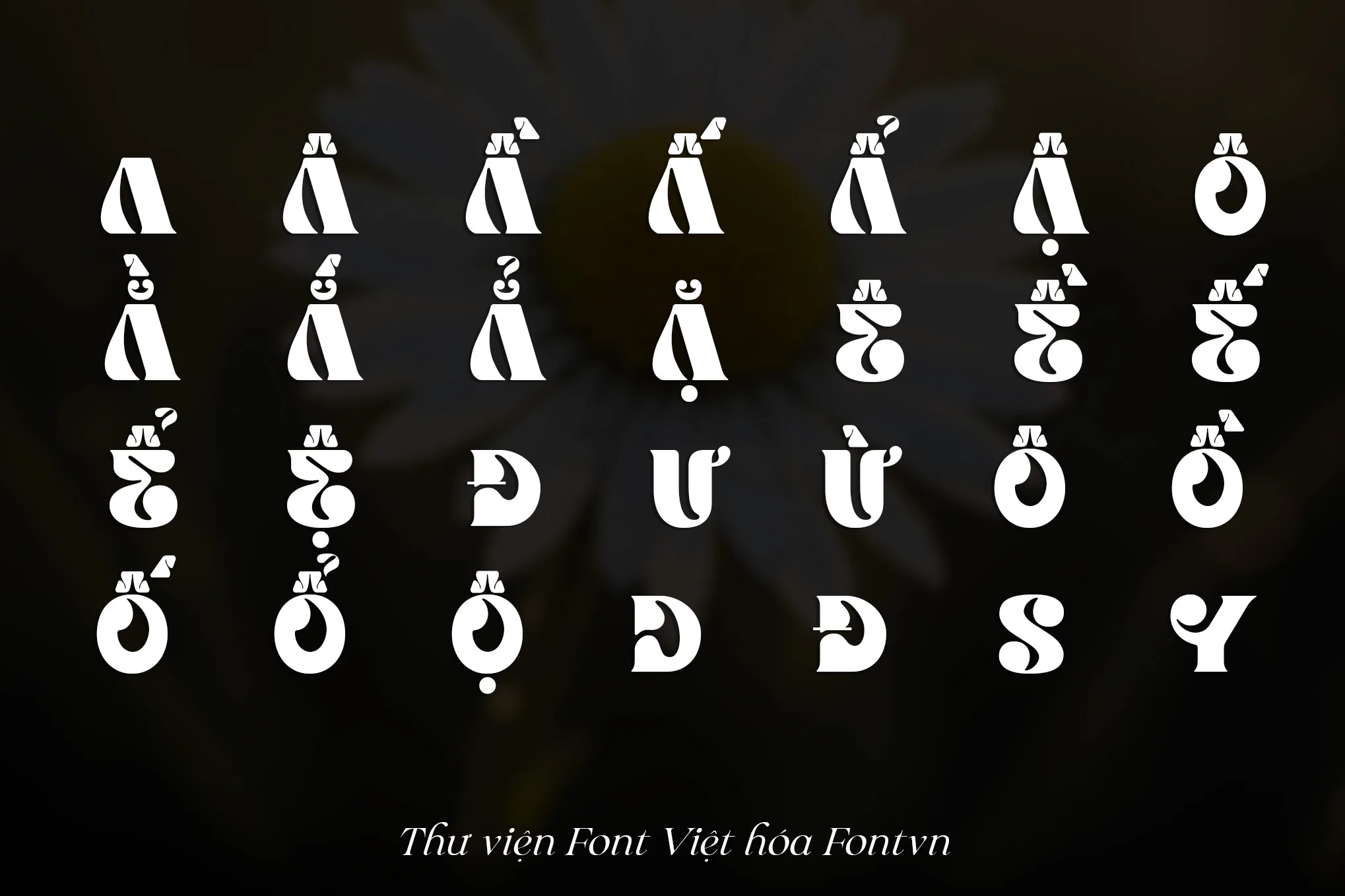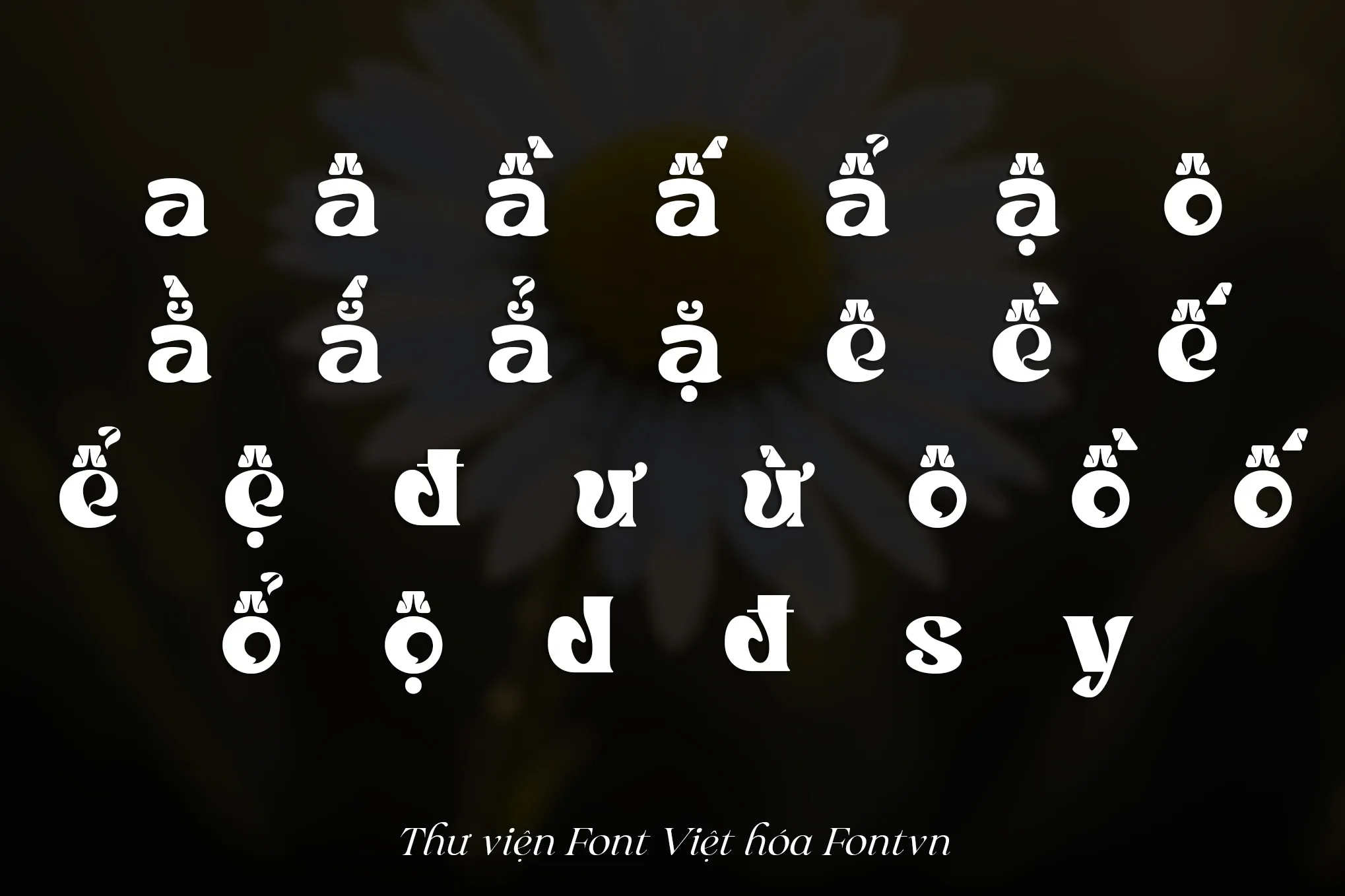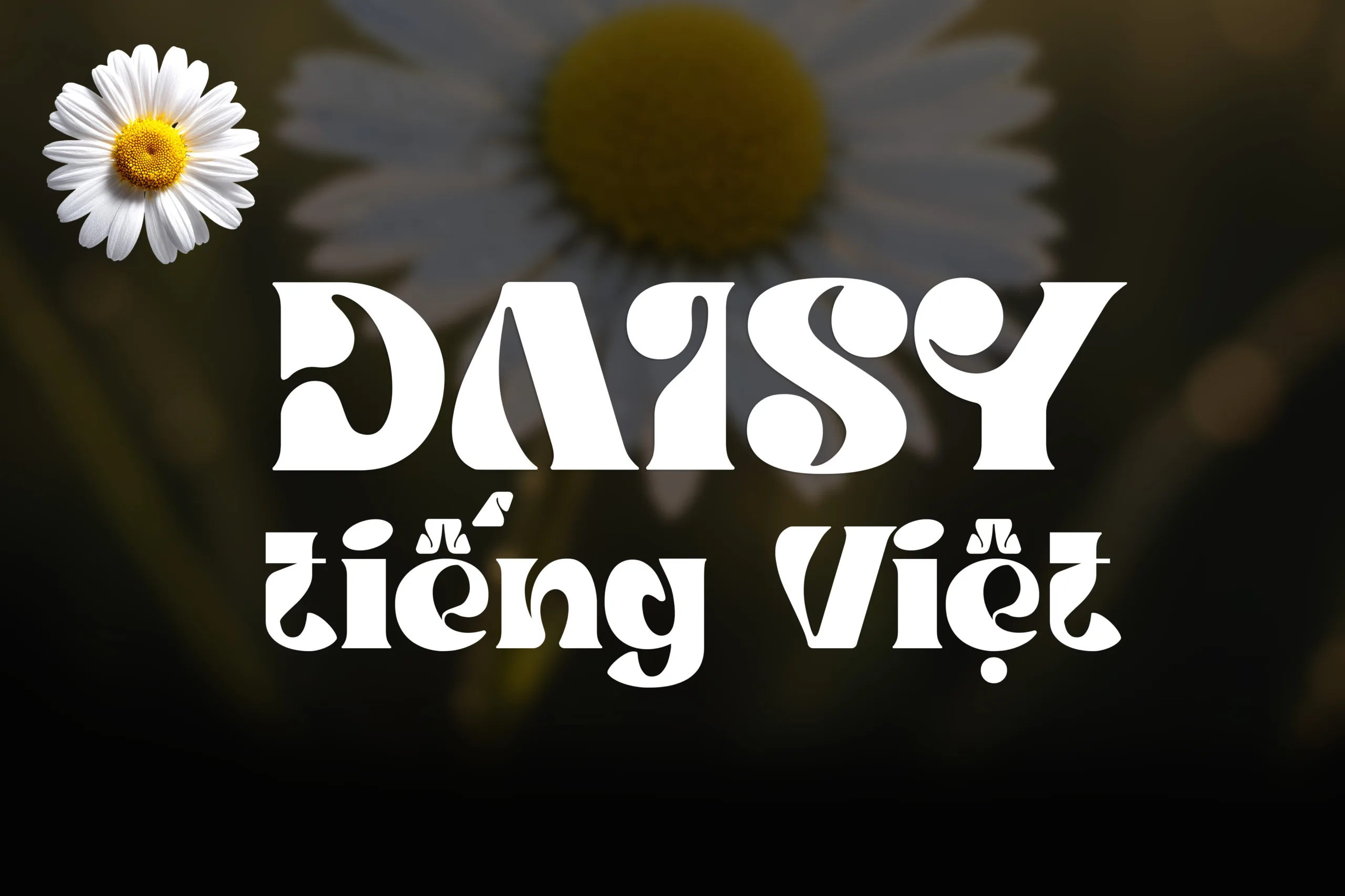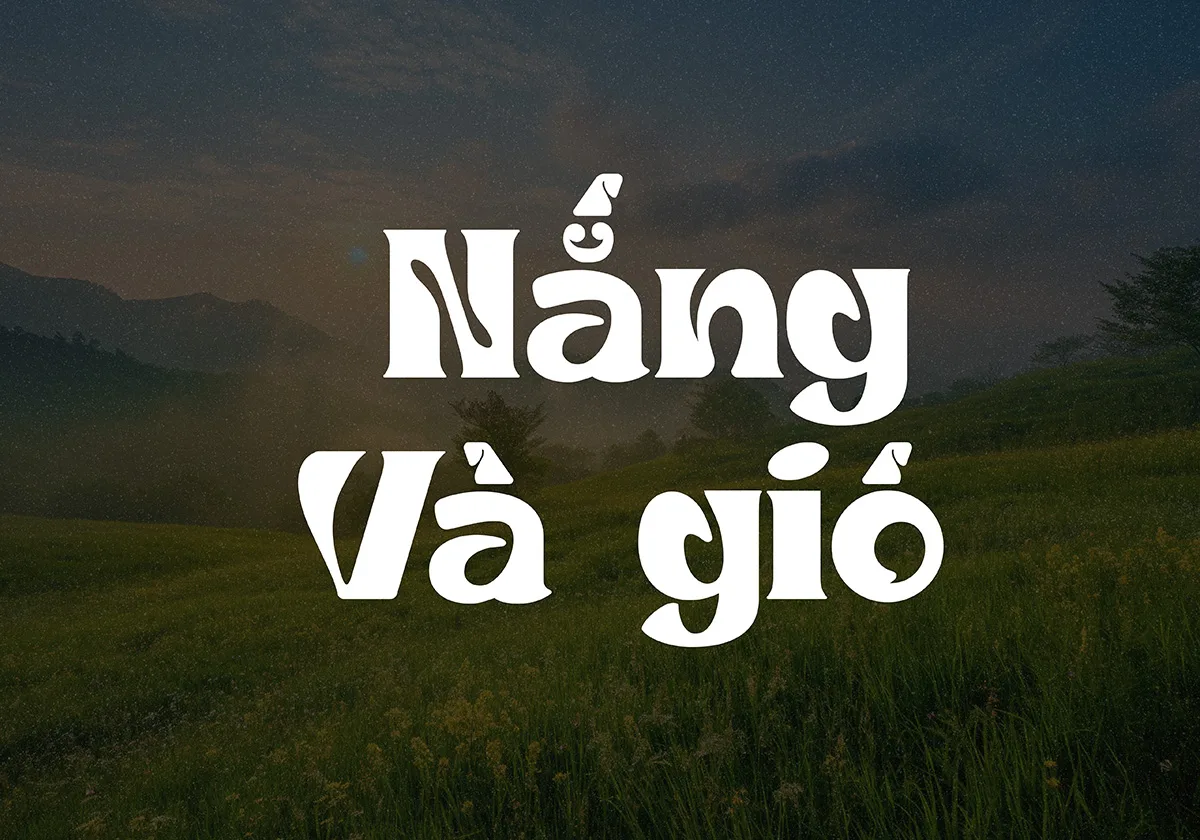
DVN Daisy tiếng Việt – Font chữ hiển thị đẹp mắt
DVN Daisy là font chữ hiển thị mang đậm cảm hứng retro hiện đại với những đường cong mềm mại, chi tiết cách điệu độc đáo và cá tính nổi bật. Thiết kế mang hơi hướng thập niên 70 kết hợp cùng phong cách đương đại, giúp tạo điểm nhấn mạnh mẽ cho tiêu đề, poster, banner quảng cáo, bao bì sản phẩm và các dự án nhận diện thương hiệu sáng tạo.
Với bộ ký tự tiếng Việt đầy đủ, DVN Daisy hỗ trợ hiển thị đẹp mắt trên nhiều nền tảng thiết kế khác nhau. Font phù hợp cho những ai muốn tạo cảm giác nghệ thuật, thời trang, vui tươi và khác biệt, đồng thời vẫn đảm bảo tính dễ đọc và thẩm mỹ cao trong các thiết kế hiện đại.